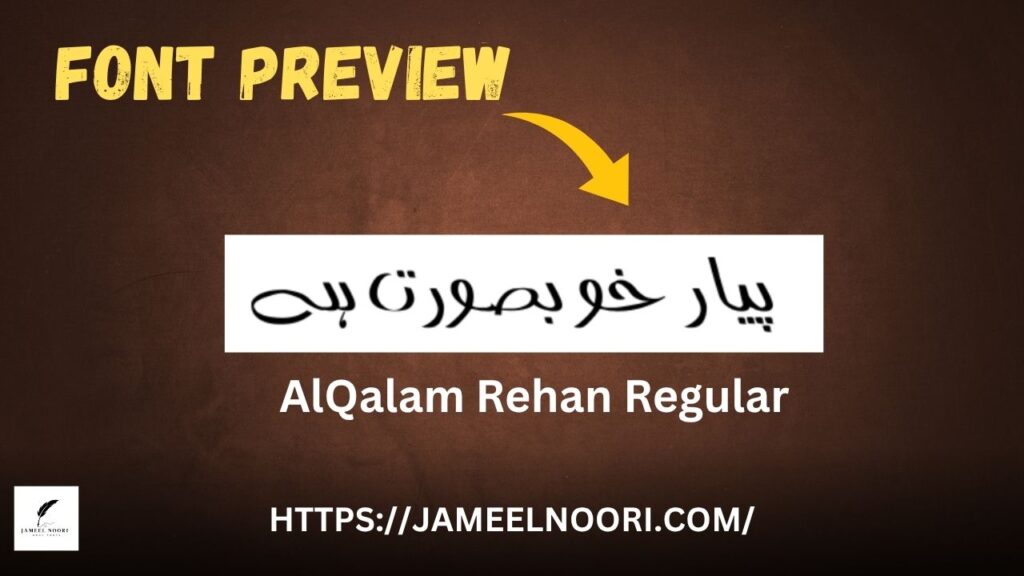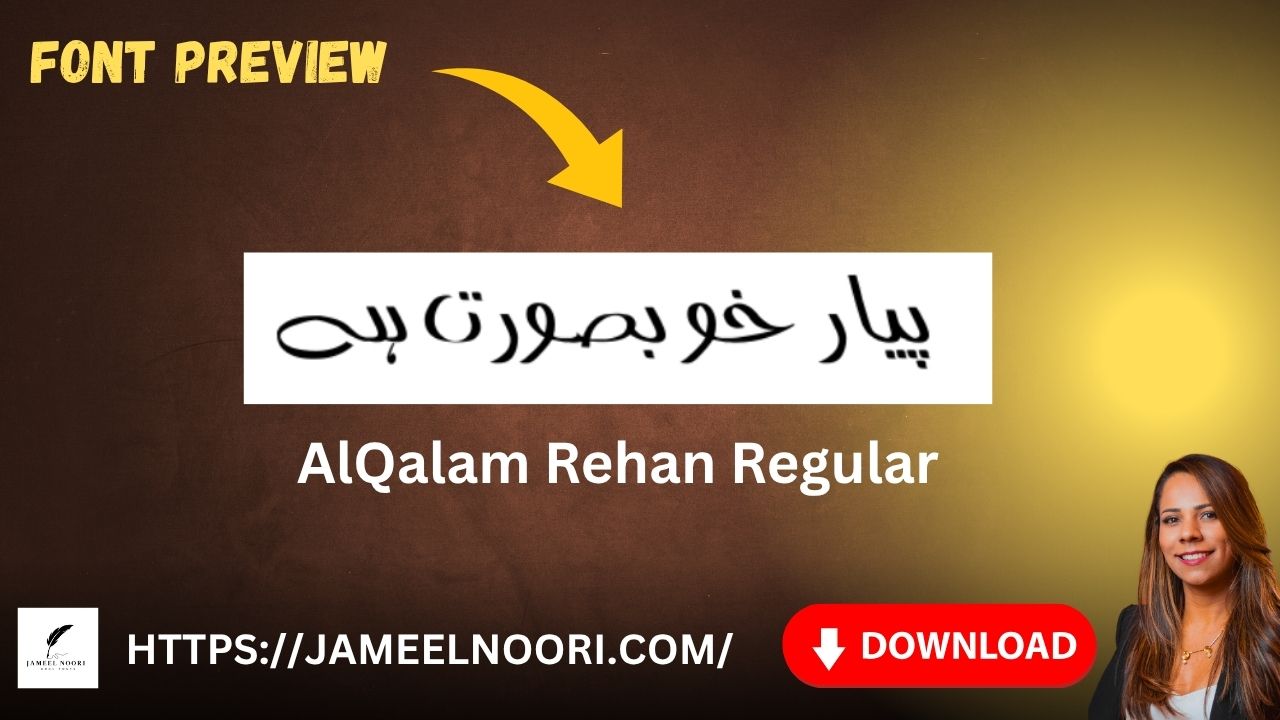
Urdu Font AlQalam Rehan Regular aik unique aur stylish Urdu TrueType font hai jo Pakistan me designers aur writers ke darmiyan bohot popular hai. Ye font readability aur elegance dono combine karta hai, isi liye ye Urdu typography ke shaukeen logon ke liye ek must-have font ban gaya hai.
What is Urdu Font AlQalam Rehan Regular?
Urdu Font AlQalam Rehan Regular aik Regular TrueType Font hai jise specially Urdu text aur calligraphy ke liye design kiya gaya hai. Ye font aesthetically pleasing aur easy-to-read design offer karta hai jo har type ke content ke liye suitable hai.
Iska smooth aur balanced design newspapers, books, aur websites me professional touch deta hai.
Key Features:
- Stylish aur readable appearance
Why Choose AlQalam Rehan Regular Urdu Font?
Agar aap apne Urdu content ko modern aur attractive banana chahtay hain to ye font best choice hai. Ye designers aur writers dono ke liye perfect hai kyunke iska alignment aur spacing professionally set hai.
Main Benefits:
- Best font for Urdu content creation
- Urdu blog aur poetry design ke liye ideal
Where to Use AlQalam Rehan Regular Urdu Font?
Aap Urdu Font AlQalam Rehan Regular ko multiple purposes ke liye use kar sakte hain:
| Usage Type | Description |
| Graphic Design | Urdu posters, banners aur flyers ke liye perfect |
| Content Writing | Urdu blogs aur articles me readability enhance karta hai |
| Education Material | Urdu books aur study guides me clean appearance deta hai |
| Social Media Posts | Facebook aur Instagram posts me stylish look deta hai |
Compatibility and Uses in Pakistan
Ye font advertisement banners, wedding cards, aur online Urdu blogs me widely popular hai.
Unique Style and Popularity
Is font ka elegant design aur fine stroke isko alag banata hai. Ye AlQalam Rehan Regular Urdu Font readability aur creativity dono maintain karta hai.
Expert Tips – Best Use of Urdu Font AlQalam Rehan Regular
Agar aap chahtay hain ke aapka Urdu content standout kare, to ye expert tips follow karen:
- Use bold font for headings aur quotes
- Combine AlQalam Rehan Regular with light background
- Use it in short Urdu poetry posts
- Maintain proper line spacing for professional look
Agar aap apne Urdu projects ko professional aur elegant banana chahtay hain, to ye font ultimate choice hai.
What type of font is AlQalam Rehan Regular?
It’s a Regular TrueType Urdu font with clean and balanced design.
Where can I use this font effectively?
In Urdu blogs, books, banners, and educational materials.
What makes this font popular in Pakistan?
Is this font suitable for social media posts?
Yes, it looks elegant and stylish for Urdu quotes or captions.